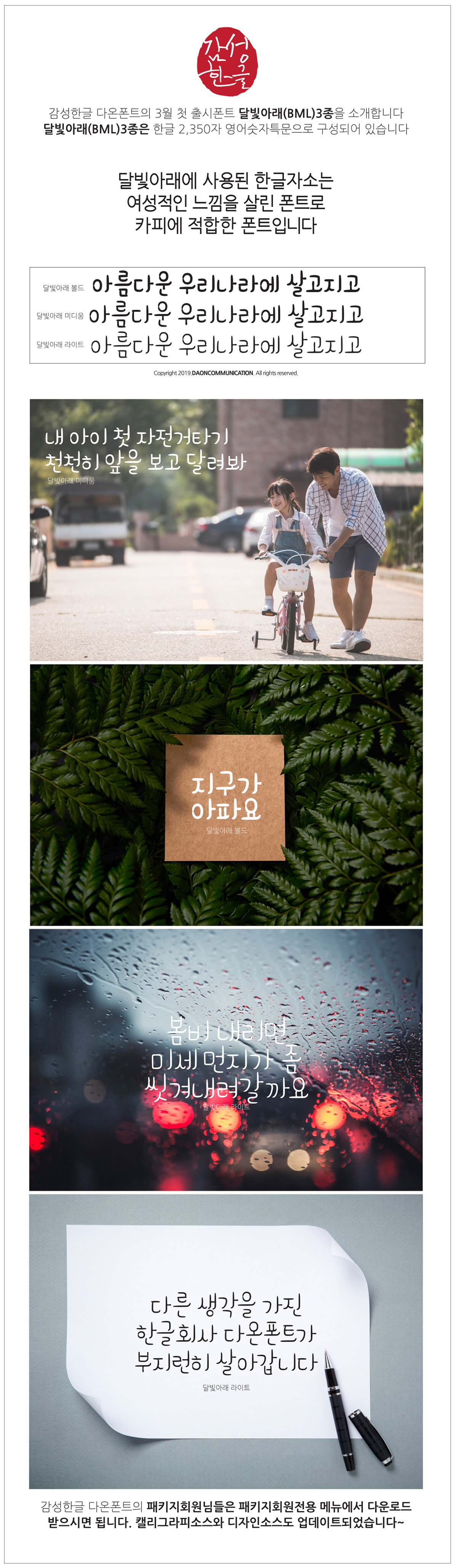
다온폰트 '달빛아래' 업데이트 안내
3월 첫 신규 업데이트 폰트를 알려드립니다.
이번 업데이트 폰트는 다온폰트 '달빛아래'입니다.
다온폰트 '달빛아래'는 3가지 버전(B,M,L)으로 출시되며
한글 2,350자와 영문, 숫자, 특수문자 일부로 구성되었습니다.
여성적인 한글 자소를 사용해 카피에 적합한 폰트입니다.